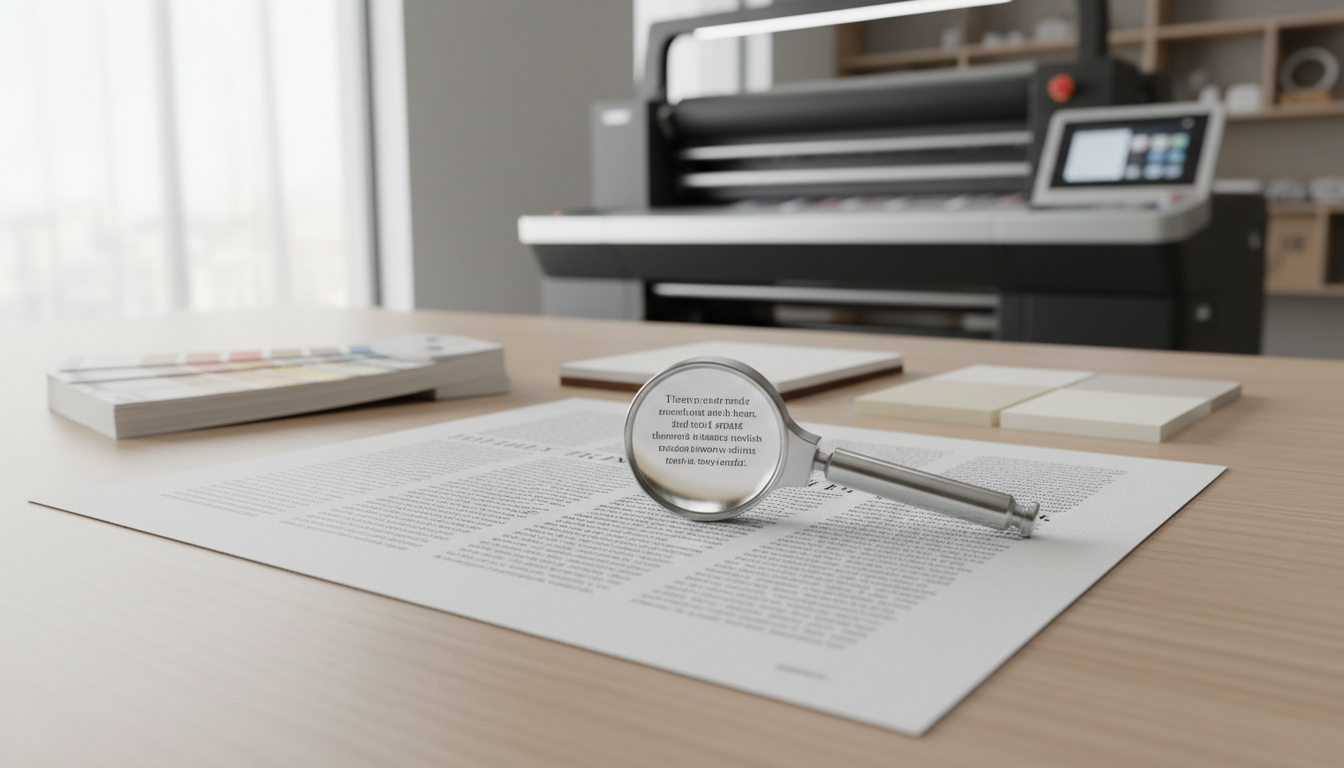
Typographie fine : jusqu’où peut-on aller en impression ?
À l’écran, tout passe.
Des polices ultra light. Des traits fins élégants. Des typos minimalistes à 0,25 pt d’épaisseur.
Et puis vient l’impression. Puis soudain :
• le texte paraît plus épais que prévu
• ou au contraire disparaît
• ou perd en netteté
• ou devient irrégulier
La typographie fine est l’un des pièges les plus fréquents en impression.
Alors, jusqu’où peut-on aller sans compromettre la lisibilité et la qualité du rendu ?
Pourquoi les typos fines fonctionnent si bien à l’écran ?
Les écrans modernes affichent :
• une lumière rétroéclairée
• des pixels très denses
• un contraste numérique parfait
• aucun phénomène d’absorption
Une typo fine semble :
• nette
• précise
• légère
• parfaitement maîtrisée
Mais l’impression n’est pas un écran.
L’impression est un transfert d’encre… sur une matière vivante
En impression, plusieurs phénomènes entrent en jeu :
• l’encre s’étale légèrement
• le papier absorbe
• la pression mécanique intervient
• la résolution réelle dépend du procédé
Ce micro-étalement s’appelle le gain de point.
Et sur une typographie fine, quelques microns suffisent à modifier le rendu.
Jusqu’où peut-on aller ? (repères concrets)
Voici des repères généralement admis en impression professionnelle :
En offset ou numérique standard :
• Texte noir simple : minimum 6 pt
• Texte en couleur : minimum 7 à 8 pt
• Filets fins : minimum 0,25 pt, mais recommandé 0,5 pt
• Typos ultra light : à éviter sous 8 pt
En réserve (blanc sur fond sombre) :
• Ajouter +1 pt de sécurité
• Éviter les graisses ultra fines
• Privilégier des fontes légèrement plus épaisses
Plus le contraste est complexe, plus il faut épaissir.
Le piège des polices “Thin” et “Light”
Les fontes modernes proposent souvent :
• Thin
• Extra Light
• Light
Ces variantes sont parfaites :
• en titrage grand format
• en affichage digital
Mais problématiques :
• en petits corps
• sur papiers absorbants
• en impression sur fond sombre
💡 Une typo fine à 6 pt sur papier offset peut devenir fragile, voire irrégulière.
Le cas critique : blanc sur fond noir
C’est là que tout se complique.
En réserve :
• l’encre du fond peut “manger” légèrement le texte
• le repérage doit être parfait
• la moindre variation devient visible
Une typo fine blanche sur fond sombre est l’un des cas les plus risqués en print.
Solution : augmenter légèrement la graisse ou le corps.
Le support change tout
Sur papier couché :
• contours plus nets
• moins d’absorption
Sur papier offset ou recyclé :
• diffusion plus importante
• micro-flou possible
• perte de finesse
Plus le papier est texturé, plus la typographie fine devient fragile.
Le rôle du noir utilisé
Un texte noir 100 % :
• est plus stable
• évite les problèmes de repérage
Un texte en noir enrichi (CMJN) :
• peut provoquer des micro-décalages
• créer un contour flou
Pour les petits textes fins : privilégier le noir simple.
Quand la typographie fine fonctionne très bien
• Titres grands formats
• Affiches visibles à distance
• Supports premium sur papier couché
• Design minimaliste maîtrisé
• Corps suffisamment grand
Quand elle devient risquée
• Corps inférieur à 6 pt
• Texte blanc sur fond sombre
• Papier très absorbant
• Impression à forte charge d’encre
• Logos ultra fins en petit format
Erreurs fréquentes observées en production
• Texte en Light à 5 pt
• Filets décoratifs trop fins
• Polices web recyclées en print
• Noir enrichi sur petits textes
• Absence de test avant tirage important
Bonne pratique professionnelle
Avant un tirage important :
✔ Imprimer un BAT réel
✔ Tester sur le papier choisi
✔ Vérifier à distance de lecture réelle
✔ Ajuster légèrement la graisse si nécessaire
Parfois, augmenter la graisse d’un seul cran ne change rien à l’esthétique… mais change tout à la lisibilité.
Ce qu’il faut retenir
La typographie fine n’est pas interdite en impression.
Mais elle doit être :
• pensée pour la matière
• adaptée au support
• testée en conditions réelles
👉 En print, la finesse extrême est toujours plus fragile qu’à l’écran.
La règle simple :
Si c’est “juste limite” à l’écran, ce sera probablement trop fin à l’impression.